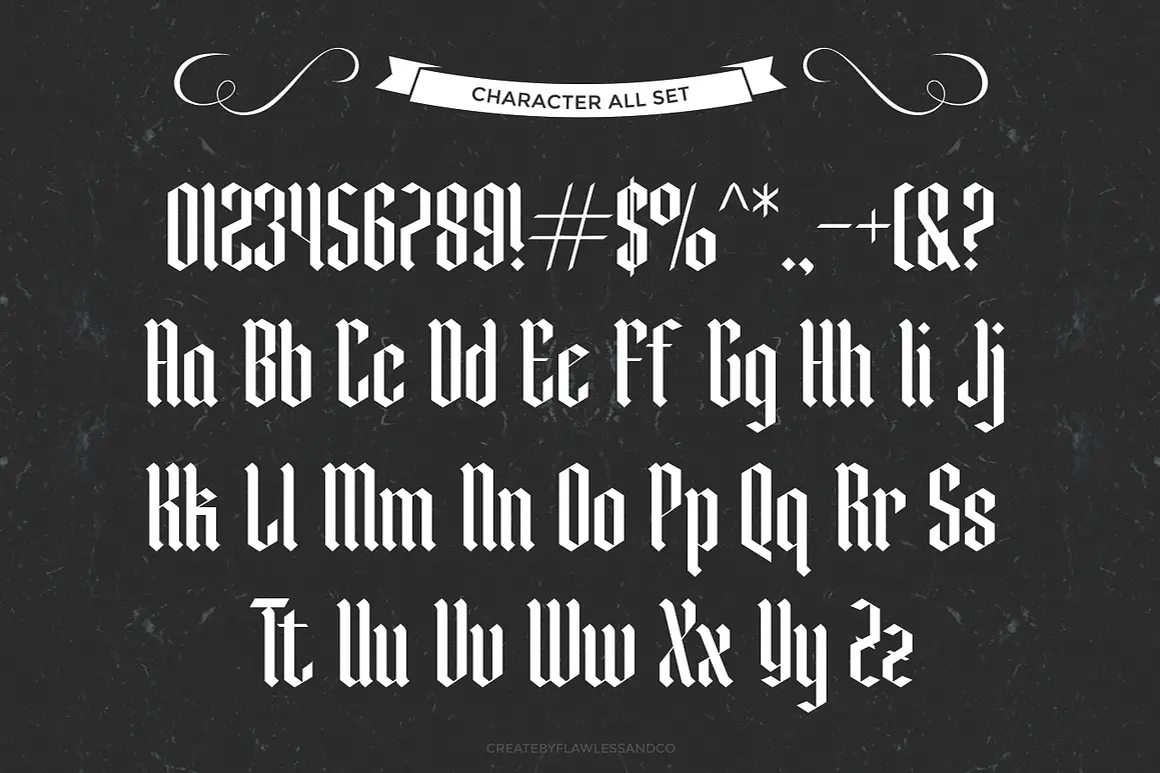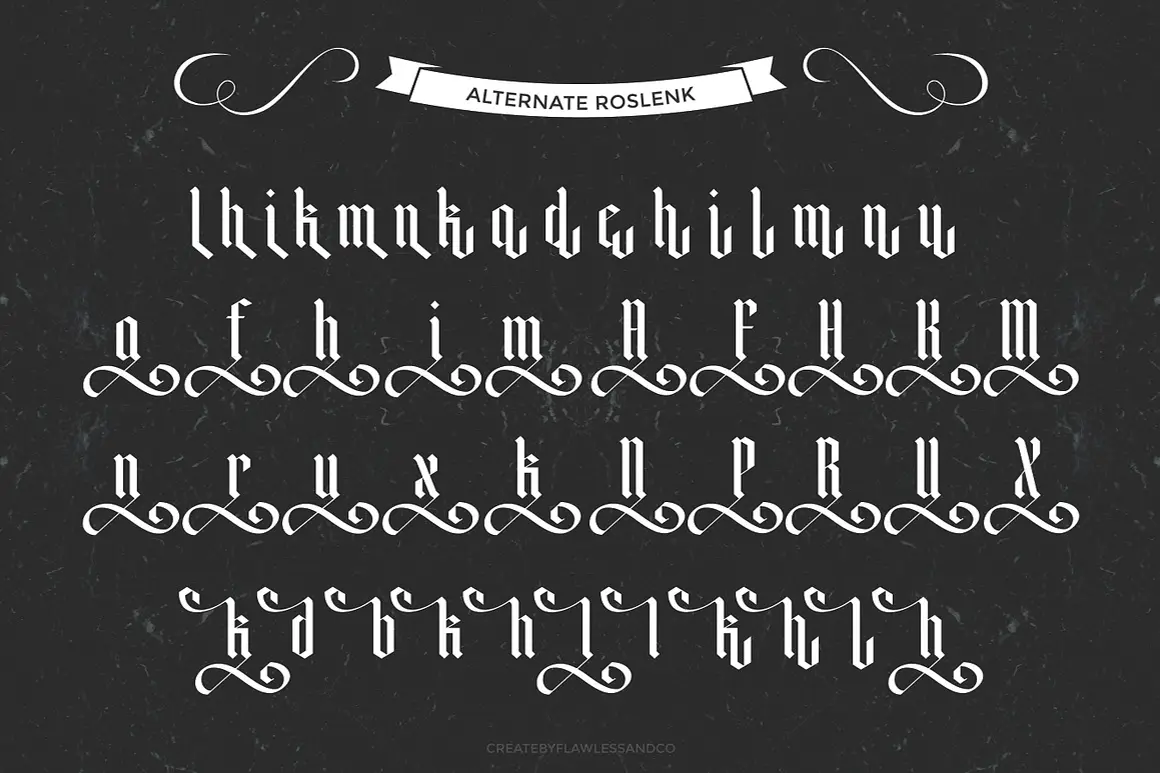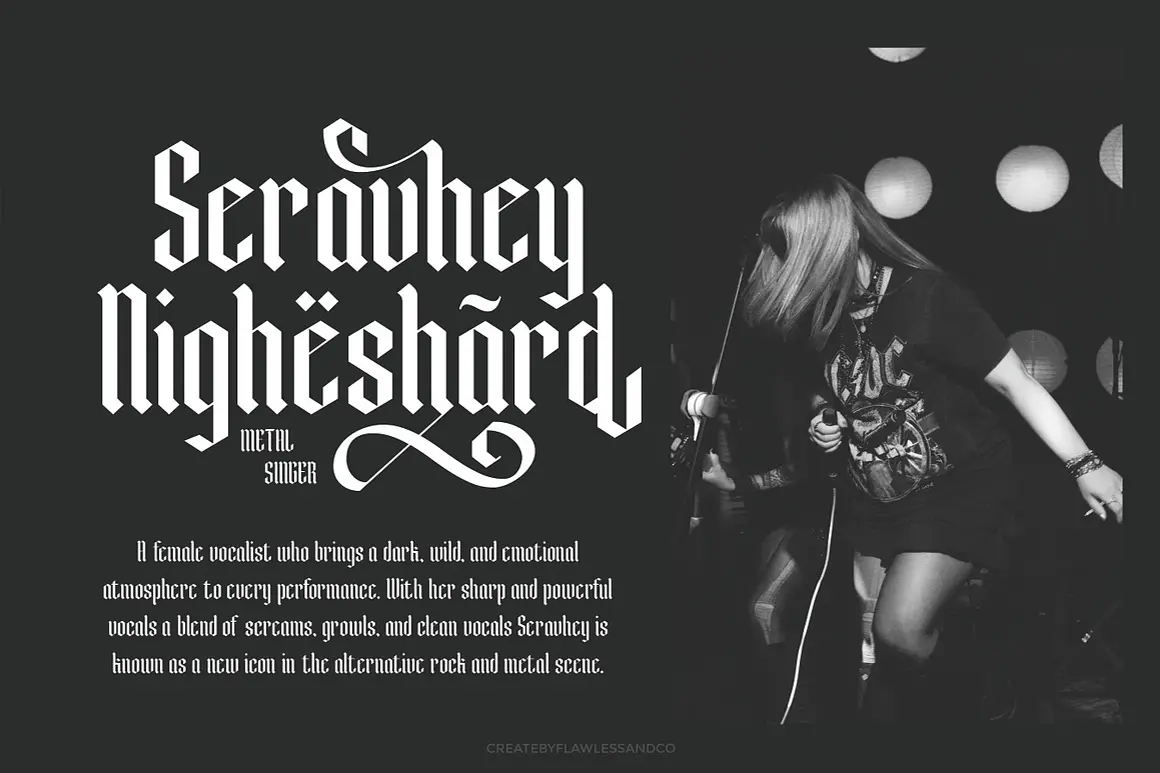
فونت بلک لتر جسور و مدرن Roslenk
Roslenk یک فونت بلک لتر دستساز با طراحی تیز، چشمگیر و ماندگار است که روح خوشنویسی گوتیک را با ظرافت مدرن ترکیب میکند. این فونت با خطوط قوی، منحنیهای خاص و جلوهای دراماتیک، انتخابی عالی برای پروژههایی است که نیاز به تایپوگرافی قدرتمند و متفاوت دارند.
✨ ویژگیهای کلیدی
- 🔠 حروف بزرگ و کوچک با طراحی منحصربهفرد
- 🔤 شامل جایگزینها (Alternates) و لیگاتورها (Ligatures) برای ترکیبهای خاص
- 🔢 پشتیبانی از اعداد و علائم نگارشی استاندارد
- 🌍 پشتیبانی کامل از کاراکترهای چندزبانه
🎯 مناسب برای استفاده در
- طراحی لوگوهای خاص، برندهای جسور و هویتهای بصری قدرتمند
- استودیوهای تتو، آرایشگاههای مردانه و برندهای خیابانی
- کاور آلبومهای موسیقی راک، پانک یا متال
- طراحی لباس، مرچندایز و برندهای فشن با هویت تاریک و خاص
- پوسترهای سینمایی، تبلیغاتی یا هنری با جلوه دراماتیک
- بستهبندی محصولات خاص، طراحی صفحات مجله و گرافیک شبکههای اجتماعی
💡 چرا Roslenk انتخابی عالی برای طراحی برند و لوگو است؟
فونت Roslenk با ترکیب سنت گوتیک و سبک مدرن، هویتی قدرتمند، خلاقانه و متمایز به برند شما میبخشد. هر حرف با شخصیت خاص خود طراحی شده تا در کنار هم، تصویری فراموشنشدنی بسازند. اگر به دنبال تایپوگرافیای هستی که هم اصالت داشته باشه و هم جسارت، Roslenk دقیقاً همون چیزیه که نیاز داری.